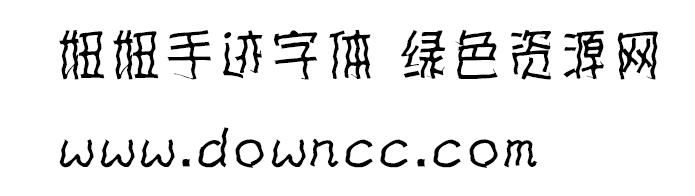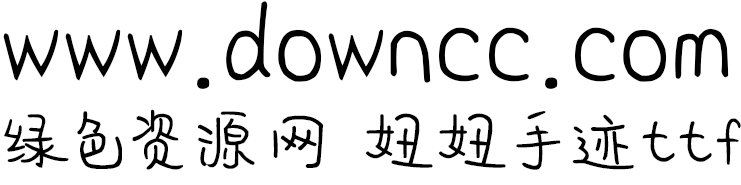
妞妞手跡體ttf是一款每一個(gè)字都扭曲的恰到好處讓你感受到最佳的視覺效果的字體樣式,通過在這款字體上添加一些特效將制作出十分具有氣勢好看的藝術(shù)字,快來綠色資源網(wǎng)下載吧!
我對這款字體十分喜愛,它在我進(jìn)行媒體藝術(shù)字制作的過程中能夠帶給人視覺上的絕對沖擊,是一款非常優(yōu)秀的字體!